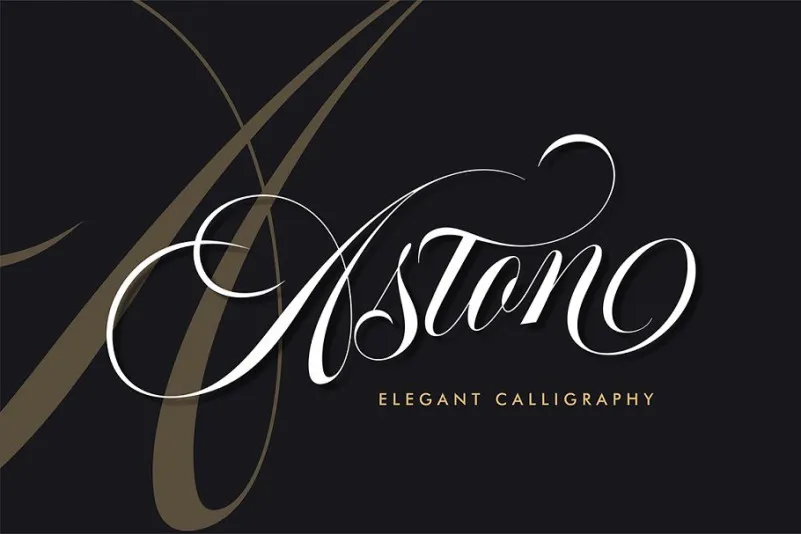
Aston Calligraphy Font – Fonte Grátis
Aston Calligraphy Font
Aston Calligraphy Font é uma elegante nova fonte de calligrafia premium que traz caracteres alternativos belos. Desenvolvida pelo designer teuku Risky Firmina, esta fonte de script é um blend de estilo de churrasco com um toque moderno da calligrafia à mão. Através do Aston Script você pode adicionar ao seu design uma pitada de sofisticação e elegância. Este tipo de fonte é perfeitamente suave, limpa, feminina e sedutora, com muitos elementos interessantes que permitem um leitura fluida mesmo entre os conectivos elaborados. Além disso, oferecemos várias alternativas de estilo para diferentes letras. Ideal para diversas aplicações formais como convites, rótulos, menus de restaurante, logomarcas, moda e acessórios, papelaria, livros e revistas, cartões de aniversário ou casamento, embalagens e etiquetas para qualquer tipo de propósito publicitário. Este script de calligrafia é uma fonte perfeita para quem busca um toque sofisticado em seus projetos gráficos.